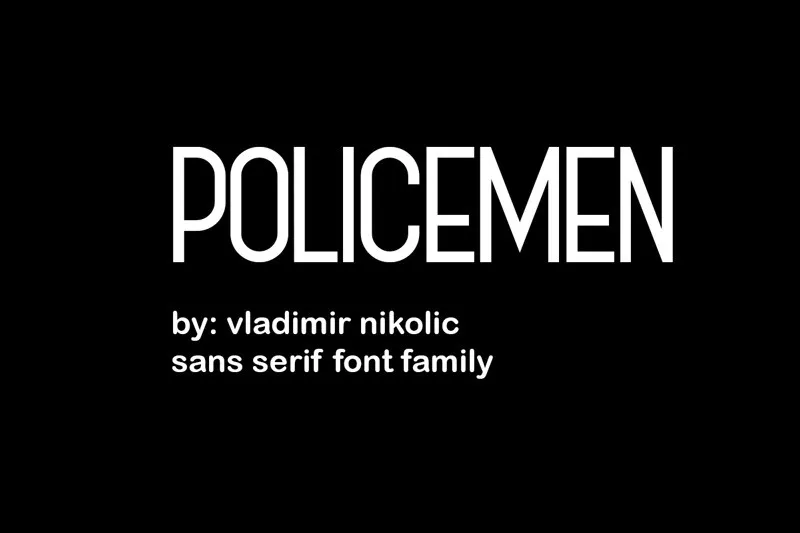
Policemen Font Family – Download Grátis
Esta nova família de fontes Policemen Sans Serif é uma paleta de linhas bem resolvida do estilo tipográfico suíço tradicional. Ela foi projetada desde o início para ser forte e moderna, sempre em sintonia com os padrões da moda. Suas linhas fortes e marcantes a tornam um recurso perfeito para criar ambientes vintage inspirados, mas também para incorporar de maneira elegante em contextos contemporâneos modernos. Com uma linha de frente firme e bem estilizada, Vladimir Nikolic desenvolveu essa fonte com o objetivo de ser impactante e atraente. O uso desta família na aplicação visual de headline, moda, revista, marca ou até mesmo para cartazes é um grande exemplo dessa proposta. As proporções contrastantes são especialmente atraentes quando utilizadas em tamanhos maiores, criando uma visão elegante e confiante que realmente destaca a mensagem. Policemen Sans Serif Family oferece mais do que apenas bom design gráfico – ela traz consigo um ar de simplicidade moderna e força contida. Uma ótima escolha para qualquer projeto que precisa ser imediatamente reconhecível, seja em editoriais ou em comunicação digital, esta fonte se destaca por sua capacidade única de atingir o público de maneira elegante sem perder a essência da mensagem transmitida.